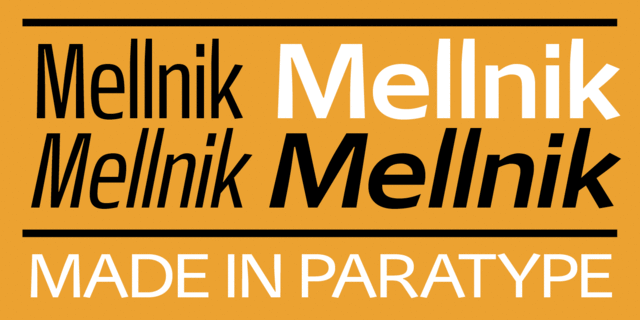
Гарнитура Мельник в духе гуманистического гротеска разработана Олегом Карпинским для компании ПараТайп в 2006 году, состоит из девяти начертаний и содержит некоторое количество альтернативных знаков. Мельником можно набирать как большие текстовые блоки в рекламных буклетах, каталогах, журналах, так и выделительные слова и фразы. Возможно использование в качестве корпоративного шрифта. Пять узких начертаний добавлены автором в 2007 году.
Ассоциации c семейством MellnikКачества и характер:
деликатный, чистый, легкий, прохладный, свежий, модный, устойчивый, серьезный, твердый, надежный, урбанистический, мужественный, сильный, тяжелый, заметный, яркий, активный, броский, стройный, высокий, ровный, простой, важный, громкий, мотивирующий, амбициозный